Abordar una historia tan larga y compleja
El presente capítulo pretende un recorrido (inevitablemente más veloz que exhaustivo) de la historia de la tipografía en las principales culturas occidentales de Europa, con la idea de que ello nos permita comprender un poco mejor el contexto de donde provinieron los primeros impresores a América.
La historia de la llegada y difusión de la imprenta de tipos móviles a los diferentes países de Iberoamérica ha sido estudiada y referida por importantes historiadores de ambos lados del Atlántico. Trabajos pioneros en nuestro continente deben verse en la obra del investigador chileno José Toribio Medina, los mexicanos Emilio Valtón y Joaquin Garcia Icazbalceta, el estadounidense Henry Wagner y los argentinos José Torre Revelo y Guillermo Furlong, entre otros. Estos investigadores sentaron precedentes importantes en un camino de descubrimientos que aun hoy está salpicado de interrogantes.
Naturalmente no es posible cubrir aquí todos los actores y acontecimientos importantes de la historia tipográfica europea. Hemos escogido los momentos que nos parecen más relevantes, por la originalidad de su aporte o por la influencia que ejercieron a posteriori. Luego del Renacimiento italiano y francés sobreviene el Barroco, de dominio holandés. El Neoclasicismo se inaugura en Francia aunque será el inglés John Baskerville quien hará un aporte significativo. España es enfocada en su momento incunable, quizás el más interesante, y (no sin pesar) soslayamos la mayor parte de la historia alemana pues pertenece a la tradición gótica, imposible de abordar aquí. Para el siglo XIX nos concentraremos en la Inglaterra victoriana y sus tipos display y para el XX hemos optado por la tipografía holandesa, sin duda la escuela más sobresaliente hoy. Muy desconocida en América, la escuela tipográfica de Europa del Este (en especial checa y polaca), es bien interesante y merece ser tratada en un contexto diferente.
Un propósito aquí ha sido ensayar una observación más íntima de la forma de las letras y de los estilos tipográficos, algo que suele ser menos abordado en los estudios de tradición bibliográfica e incluso en textos de tipografía para comunicadores visuales. Creemos que adentrarse en la historia de los protagonistas de la evolución de las letras impresas es una buena oportunidad para asimilar sus aspectos formales y estilísticos más sutiles.
También hemos señalado bibliografía específica allí donde nos parece valioso, para que el lector interesado continúe su exploración. Existe aun poca bibliografía tipográfica en español y portugués, y la mayoría de las referencias provienen del inglés.1 Finalmente y con espíritu didáctico, al final de la 2da parte, ha sido dispuesta en recuadros separados del relato principal, información sobre anatomía y evolución de las formas tipográficas.]
Alemania: tipos móviles e impresores móviles
Parece una justa ironía el que los primeros impresores con tipos móviles hayan tenido ellos mismos que emigrar de sus ciudades alemanas hacia otras comarcas, dado lo amenazante de su invención. Para la Iglesia los artistas negros representaron un riesgo doble: político-ideológico, por pretender imprimir versiones “no oficiales” de la Biblia, y político-sindical ya que los scriptoria de los monasterios podían perder gran parte de su “mercado editorial”.
Hay quienes atribuyen la invención del tipo móvil de metal al impresor holandés Lorenzo Coster. Pero más allá de esta discusión histórica, resulta sensato imaginar que cualquiera la nacionalidad de quienes hubieren perfeccionado el procedimiento de fabricación de tipos móviles, inventados en China en el siglo XII, el destino migratorio del oficio no habría sido muy diferente. Migración e intercambio cultural fueron, junto a la moda, los motores primordiales de “evolución” de las formas tipográficas en Occidente. Fue la migración alemana a otros países europeos lo que posibilitó la difusión del tipo móvil, así como en muchos casos el protagonismo recayó en extranjeros inmigrantes en otras culturas. De modo que hablar de historia de la tipografía implica hablar de sucesivos liderazgos económicos, de persecuciones religiosas, de intercambios e influencias culturales, de estilos nacionales, nacionalismos, chovinismos y hasta de copias e inescrupulosos plagios.
Los tres tipos de góticas
Gracias a la minucia de investigadores bibliográficos, conocemos hoy los usos a los que se destinaron los estilos tipográficos en los albores de la imprenta de tipos móviles en Europa. Si resulta oportuno revisitar brevemente esos estilos la distinción de Alfred Forbes Johnson 2 de tres grupos de góticas resulta muy provechosa:
1 Gótica Textura. Un tipo de letra muy vertical, esbelta y angular, extremadamente geométrica, y de pies pronunciados en forma de rombo o diamante. Destinada a obras litúrgicas, es el tipo de letra utilizado por Juan Gutenberg (c.1398-1468) en sus biblias de 42 y 36 líneas y en todos los misales antiguos. Se continuó usando para ello durante todo el s. XV e incluso esporádicamente en el s. XVI. Para ese entonces la gótica rotunda fue el estilo de moda, y para la época de la Reforma la textura casi no se destinaba sino a títulos y usos display (poco texto, cuerpos grandes). 3
2 Gótica Romanizada (o Fere-Humanistica). Los impresores de textos clásicos, escolásticos y teológicos en latín buscaron un estilo de letra menos formal que la textura, y hallaron su inspiración en los manuscritos: un estilo gótico con tendencias humanistas, cultivado por los primeros humanistas italianos, en particular Petrarca. Como no posee los pies romboidales de la textura, pero tampoco los serifs contundentes de las letras humanísticas, este estilo es visto como transicional. De igual modo, sus signos son más diferenciados entre sí de lo que son en el estilo textura (lo cual supone una mejor lecturabilidad), pero aun no tienen la redondez de las romanas. Ha sido también llamada “Fere-Humanistica” o “Gotico-Antiqua”. En castellano “Gótica romanizada” nos parece una buena fórmula. Dada su diversidad estilística este grupo de góticas es el más difícil de definir, en una época donde los estilos se prestaban rasgos entre sí. Sin embargo existen buenos ejemplos de estas góticas romanizadas: el segundo tipo fundido por Schweynheym y Pannartz (1468), impresores en Subiaco, es un gótico romanizado. También hacia 1475 el alemán Ulrich Gering creó, desde su taller Soleil d’Or, algunas góticas romanizadas muy bellas.
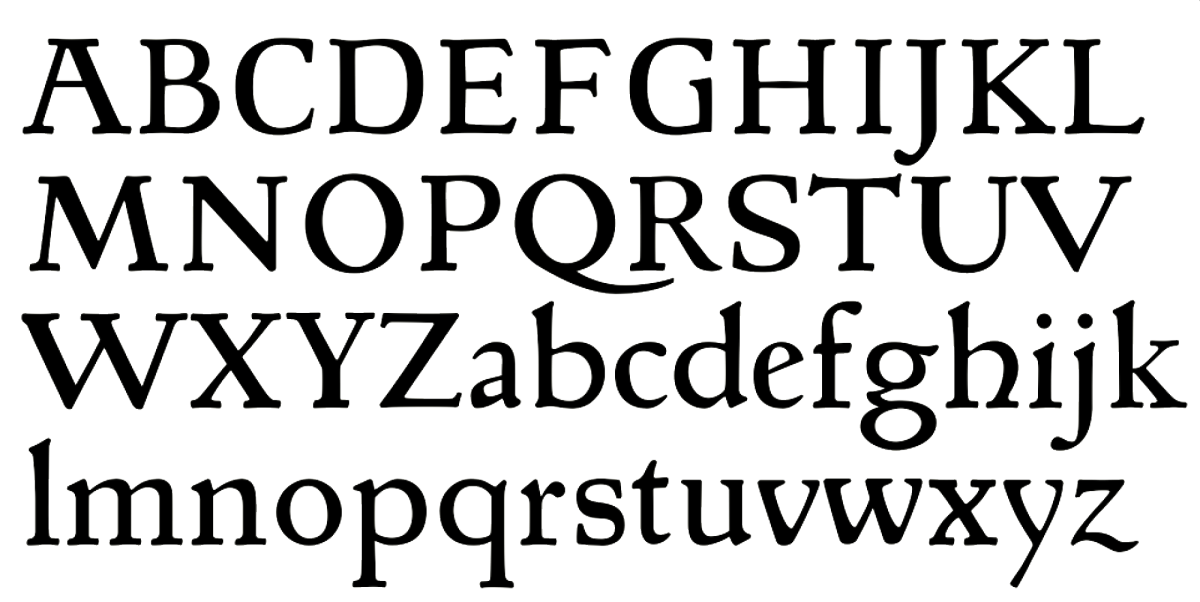
Tipo de Ulrich Gering de 1476: ejercicio de rescate histórico hecho por alumnos en taller dirigido por Alejandro Lo Celso y Philippe Millot, en la ENSAD École Nationale Supérieure des Arts Décoratifs, París, 2007.
Hubo varios intentos de rescate de este estilo: los célebres aunque poco felices tipos Troy y Chaucer de William Morris (fines del s. XIX); el revival del propio tipo de Subiaco hecho por St. John Hornby para su imprenta londinense Ashendene en 1902; el tipo Treyford, una interpretación literal de la caligrafía de Petrarca, diseñado por Graily Hewitt para la imprenta de la Universidad de Oxford en 1929 (severamente desacreditado por Stanley Morison en The Fleuron VII, p.180). Las góticas romanizadas se usaron un breve período pero fueron pieza clave en la evolución de los estilos. Entre 1459 y 1485 se produjeron hermosos incunables en góticas romanizadas. E inmediatamente sucedió la gótica rotunda, de gran preferencia entre los impresores de España.
3 Gótica Rotunda. Este tercer grupo de góticas es la “versión” italiana de las góticas texturas, y al parecer fue muy popular en Florencia. Una letra francamente más redonda que la textura (letras c e o b d p q), sin su pie diagonal de base, y a diferencia de la tendencia humanística de las góticas romanizadas, la a está cerrada y la g adopta la típica forma angular, mientras ascendentes y descendentes se acortan bastante. Según Johnson el ámbito paleográfico les ha llamado letras “boloñesas” por su uso en la escuela de leyes de la Universidad de Bolonia, aunque también se les ha denominado “venecianas”. Para nosotros hoy “veneciana” significa “romana” en el sentido de las primeras antiguas humanísticas, como la romana de Nicolás Jenson. Sin embargo para el ojo del s. XV las góticas rotundas de Jenson eran mucho más familiares que su romana, una forma nueva y sofisticada a la que aun era preciso acostumbrarse. Johnson demuestra que, hacia el final del siglo, las góticas rotundas toman el lugar de las góticas romanizadas en los cuerpos pequeños, mientras que comienzan a competir con las góticas texturas en título y formas display.
Italia y las letras humanistas: de Petrarca a Bracciolini
Los estilos tipográficos que hoy llamamos humanistas surgieron como rescate de la legendaria minúscula carolingia del siglo VIII d.C. (en realidad de sus versiones tardías de siglos XI y XII), último momento de la historia europea al que los renacentistas veían asociada una cierta unidad político-cultural. Creada a pedido del emperador Carlo Magno por un grupo de eminentes calígrafos coordinados por el sajón Alcuino de York, la minúscula carolina fue impuesta como “estilo de la casa” por decreto imperial en el 789 d.C. Podríamos decir que se trata del primer “diseño de letra personalizado”.
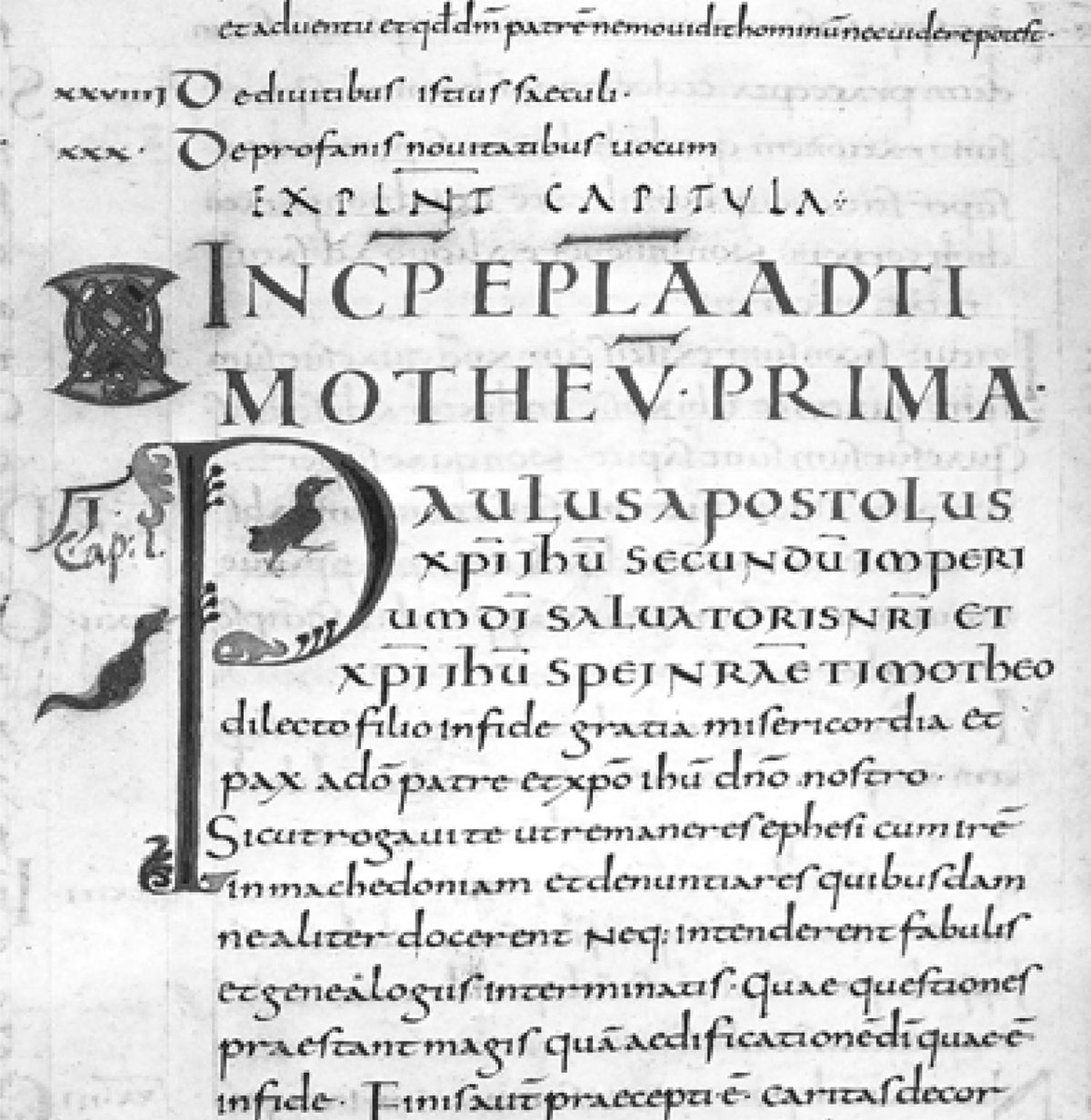
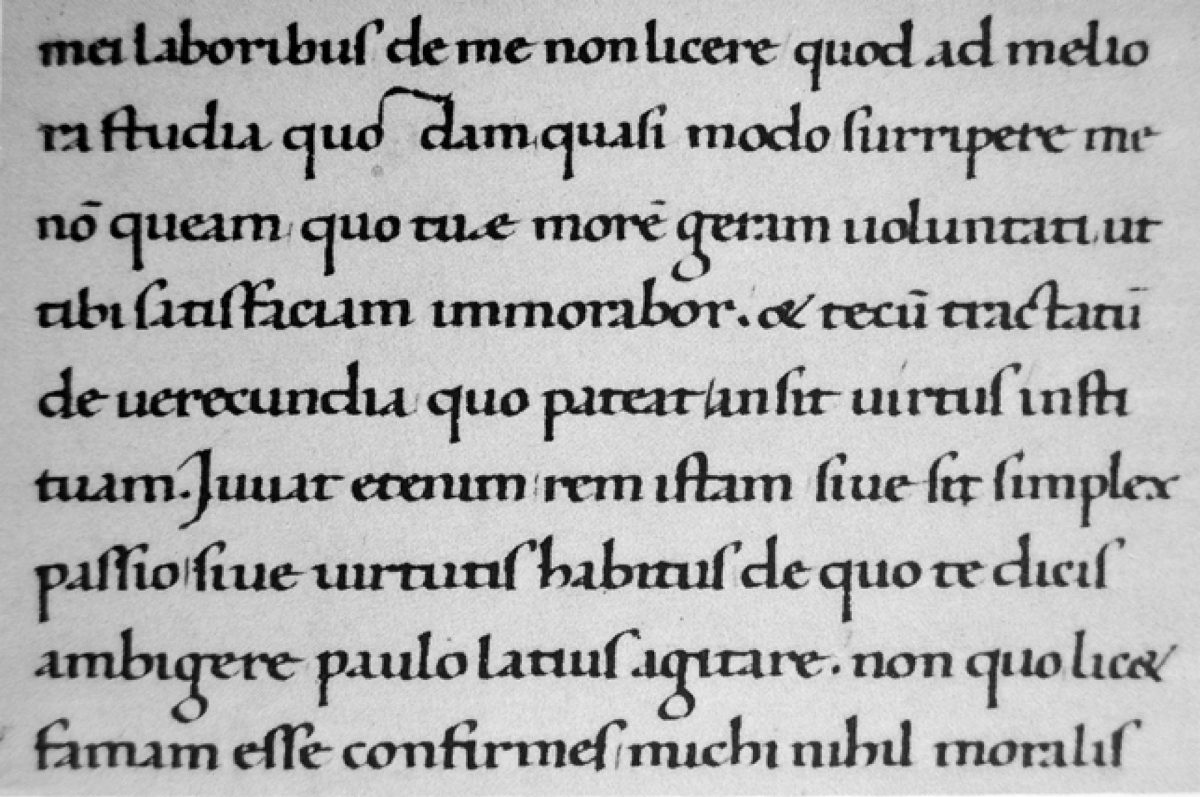
Petrarca (1304-1374) fue el precursor de esa admiración por la carolingia, la reflejó en su propia letra de copista y la llamó “lettera antica” en oposición a los modelos medievales vigentes en su época. A partir de su influencia y la de sus discípulos –Coluccio Salutati (1330-1406), discípulo de Petrarca; y Poggio Bracciolini (1380-1459), discípulo de Coluccio–, los estilos caligráficos de los manuscritos italianos del siglo XV, inspirados en los manuscritos carolingios, alcanzaron singular belleza, demostrando la devoción de los humanistas al combinar sus ideales románticos con sus capacidades artísticas. Hacia 1400 Poggio Bracciolini escribe una nueva lettera humanistica, muy inspirada en las carolingias de los siglos XI y XII. De acuerdo a Donald Anderson 4, ese es el corazón de nuestro alfabeto minúsculo. Sin apuro este estilo convivió durante casi un siglo con la gótica rotunda y con varios estilos de bastarda, una gótica itálica típicamente francesa.
La segunda aportación de Poggio es altamente valiosa. Como es sabido, el estudio de las mayúsculas obsesionó a los renacentistas. Con la idea de alcanzar la letra “perfecta” arquitectos, artistas y diseñadores buscaron (en todos los casos forzadamente) amoldar las estructuras de las capitales a retículas geométricas: Feliciano, Alberti, Da Moyle, Schedel, Pacioli, Fanti, Torniello, Durero, Verini, Tory, Tagliente, Palatino, Neudörffer, Fugger, Wyss, Yciar, Ruano, Cresci, Horfei, Rossi y Antonozzi son los nombres significativos de esos esfuerzos entre el siglo XV y el XVII. 5
De cualquier modo es evidente que estas mayúsculas, construidas a partir de proporciones geométricas (o más bien a la inversa), más que letras eran intelectualizaciones de letras. Sus contornos eran dibujados y luego rellenados de tinta. No era posible escribirlas en manuscritos. De acuerdo a Anderson, Poggio Bracciolini es quien, después de estudiar las capitales talladas en inscripciones epigráficas, desarrolla una versión caligráfica, en una escala apropiada para las minúsculas y trazadas con la misma pluma. Esto es un hito fundamental en la historia del alfabeto romano: mayúsculas y minúsculas comienzan a convivir en una página como dos subsistemas de escritura.
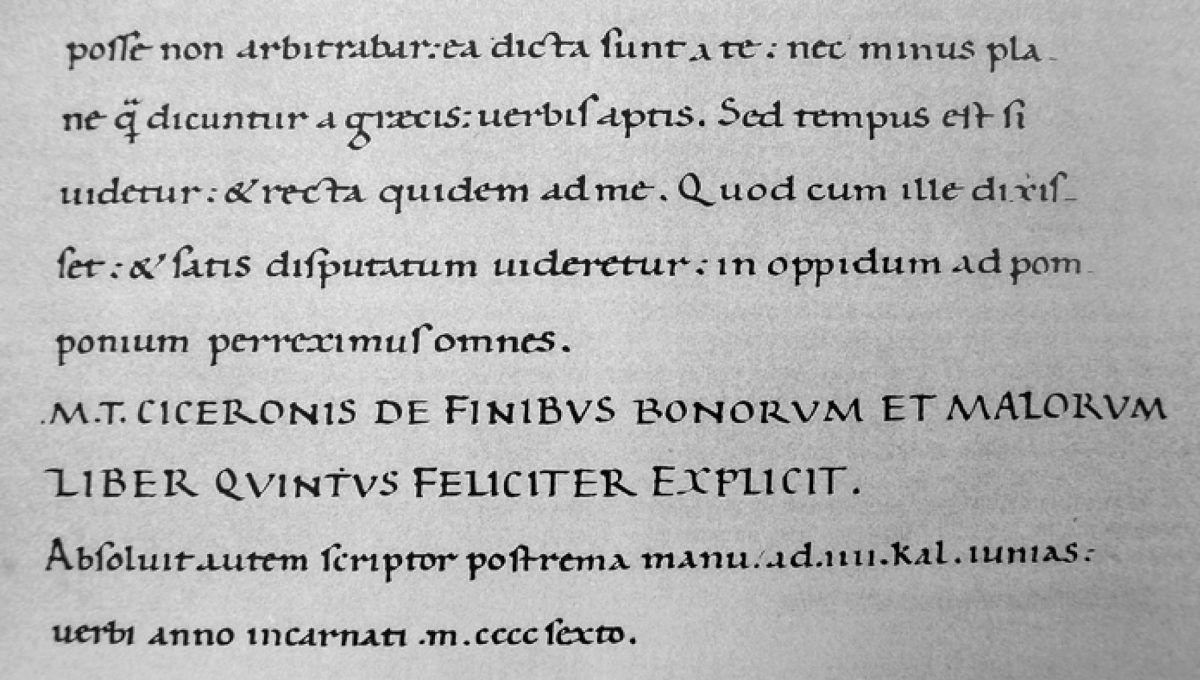
La itálica de Niccolò Niccoli
El comercio floreciente de libros manuscritos creó en Italia un sistema de fama y prestigio para los editores de libros así como para los escribas que eran empleados en las casas editoriales. Entre los nombres asociados a la minúscula humanística está también el de Niccolò Niccoli (1363-1437), quien al permitirse introducir en la minúscula cierta rapidez y espontaneidad logró el estilo que hoy denominamos “itálica”. Niccoli y Poggio abrieron así el camino a las dos interpretaciones de la minúscula humanística que se convertirían en los dos grandes estilos italianos del siglo XV, base de nuestra escritura tipográfica: la redonda y la cursiva.
Otros maestros escribas como Pietro Cennini (1462-1481) y Antonio Sinibaldi (1443-1528), ambos de Florencia, Marcus de Cribellarus de Venecia y, más notablemente, Bartolomeo Sanvito de Padua (1435- c.1520), contribuyeron al refinamiento de una caligrafía cursiva. Esta cursiva encontraría en 1500, por iniciativa de Aldo Manucio en Venecia, su primer molde en tipos de metal.6 Adobe Sanvito, una agraciada itálica humanista apenas inclinada, es homenaje de Robert Slimbach al gran calígrafo Bartolomeo Sanvito.
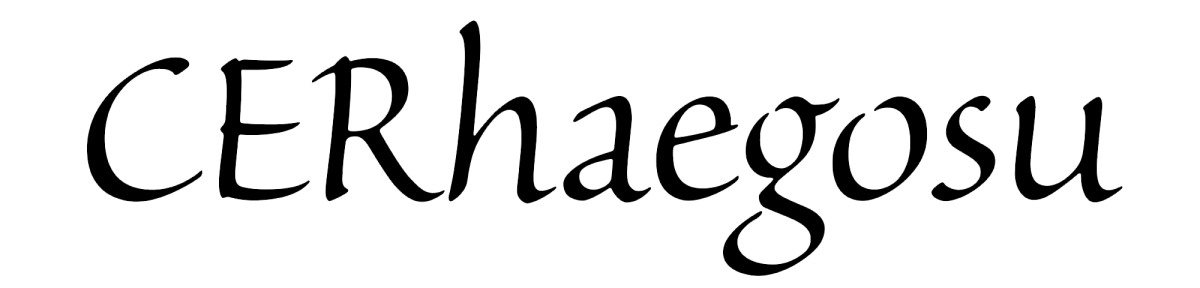
Adobe Sanvito, 1993, tributo de Robert Slimbach al calígrafo renacentista Bartolomeo Sanvito.
La escuela veneciana y Nicolás Jenson
Se cree que antes de 1500 ya había imprentas en unas 75 poblaciones italianas. Pero era Venecia la que ofrecía el mayor atractivo para los impresores. Una ciudad refinada y próspera en su comercio con Oriente, donde había importantes bibliotecas y residían muchos coleccionistas de manuscritos. Enviado por su protector el rey Carlos VII de Francia para interiorizarse con el arte negro en Maguncia, el francés Nicolás Jenson se encontró de regreso en París con una doble mala noticia: Carlos VII había muerto y su hijo el nuevo rey Luis XI no se interesó en admitirlo en la corte. En 1470 Jenson se establece en Venecia, y en poco tiempo se convierte en uno de los impresores más admirados.
Si bien hubo varios intentos de producir tipos en base a estilos caligráficos de la época –los hermanos alemanes Juan y Wendelin de Spira así como el mismo Jenson produjeron varias rotundas admirables–, es claro que la minúscula humanista era percibida como el estilo más apropiado para ediciones escolásticas.
De todos los intentos de colar un tipo en plomo que interpretase fielmente el espíritu de la mínúscula humanística es el de Nicolás Jenson el más logrado. Jenson abrió los espacios dentro y fuera de las letras y les dio a las contraformas un agradable efecto sereno y orgánico, obteniendo un ritmo muy armónico en la línea de texto y en la mancha tipográfica. Hasta su muerte en 1480, Jenson imprimió unos 150 libros, algunos extremadamente bellos, y sus páginas son hoy para muchos las más hermosas de la historia del libro occidental.
Por ser tan admiradas, ha habido innumerables rescates históricos de las venecianas. El talentoso Frederic Goudy se dedicó con fervor a ello. Sus tipos Deepdene y Berkeley Old Style son hermosos ejemplos de venecianas, interpretadas con el sentido de amigabilidad tan típico de Goudy. 7
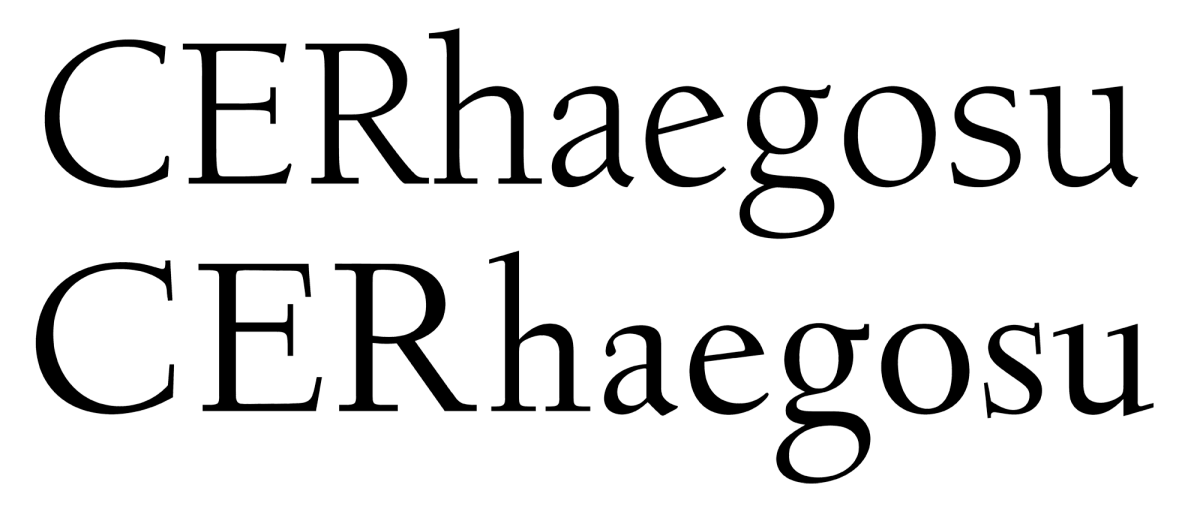
Dos grandes diseños de Frederic Goudy de inspiración veneciana: Berkeley Old Style [1914, versión digital ITC + Adobe 1989] y Deepdene [1927, versión digital Lanston 1992].
La veneciana de Jenson en particular también ha sido muy revisitada. Ya mencionamos los intentos (poco logrados) de William Morris.
El tipo Centaur del norteamericano Bruce Rogers (1870-1957) ha sido el más citado en la literatura tipográfica del siglo XX, aunque a nuestros ojos resulta inocente, por construir una letra aun más caligráfica que la del propio original. 8
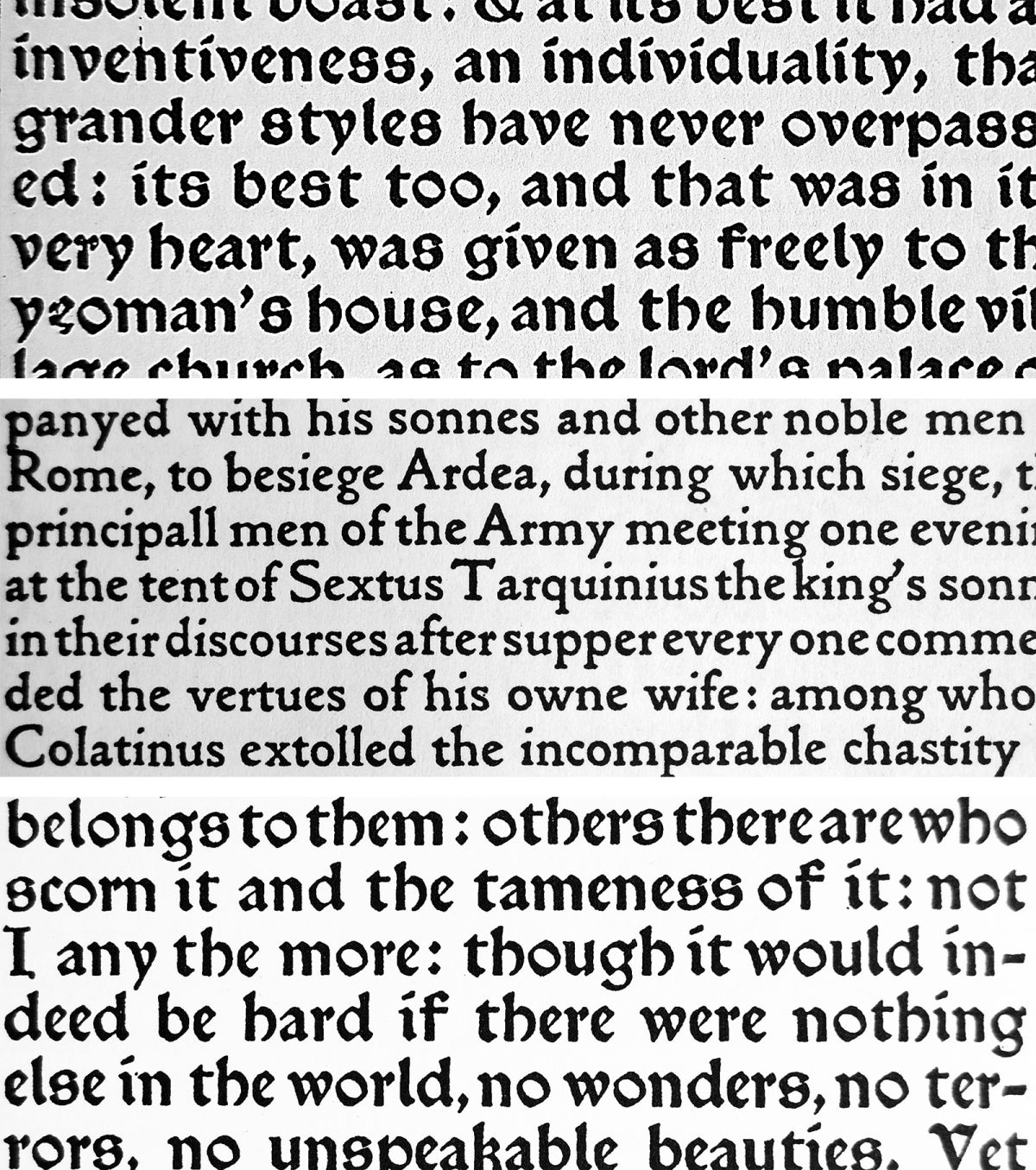
La interpretación digital de Robert Slimbach, Adobe Jenson, nos parece más justa con el espíritu jensoniano a la vez que más apropiada a ojos contemporáneos. Finalmente, una inquietante interpretación contemporánea es el tipo Lucrecia (no publicado) de Óscar Yáñez, egresado de la Maestría de diseño tipográfico del Centro Gestalt de Veracruz, México, 2007.
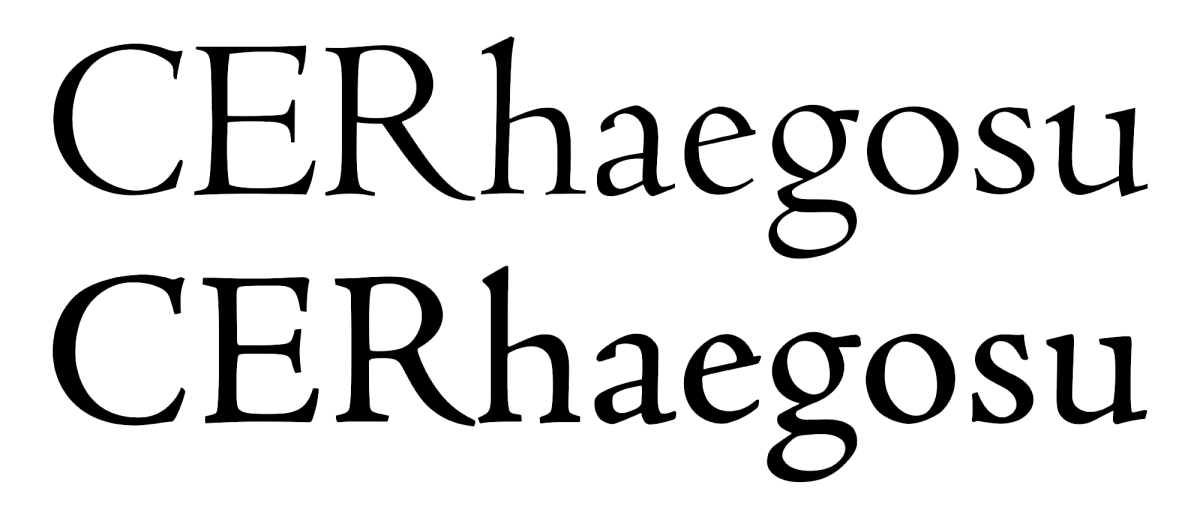
Monotype Centaur, de Bruce Rogers, 1915 [versión digital de Adobe, 1991] y Adobe Jenson de Robert Slimbach, 2000.
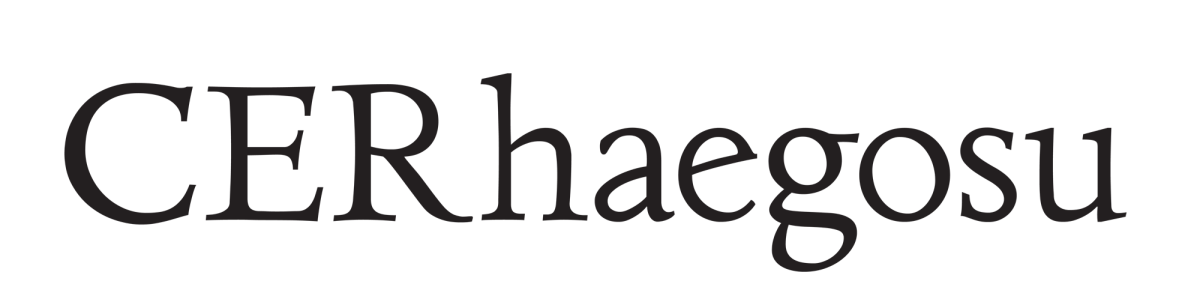
Tipo Lucrecia de Óscar Yáñez, 2007 [no publicado].
Francesco Griffo y la imprenta aldina
Aldo Manucio es con justicia recordado como el “Príncipe de la Imprenta”, por la belleza y refinamiento de sus ediciones y por la importancia de las innovaciones editoriales que introdujo. En 1495 estableció su taller en Venecia e inmediatamente publicó, nada menos que, los primeros libros impresos en griego. También en 1495 Manucio publica la obra De Aetna del cardenal Pietro Bembo (personaje central del intelecto veneciano y autor de las celebradas cartas románticas a Lucrecia de Borgia). Para este libro Aldo contrata los servicios del joyero de Bolonia, Francesco Griffo, quien graba los caracteres que hoy conocemos como tipografía Bembo (la de Monotype por ejemplo). Cuatro años más tarde la sensibilidad de Griffo con la letra humanística estaba más depurada. Su nuevo diseño (hoy Poliphilus) se usó en la renombrada obra de Francesco Colonna, Hypnerothomacchia Poliphili, obra mítica del Renacimiento. Por vez primera en un impreso las capitales (de inspiración epigráfica) estaban bien armonizadas con las minúsculas, logrando un bello ritmo blanquinegro en la línea de texto. Además las ilustraciones estaban armonizadas con las manchas de texto, logrando un efecto único.
El paso de Jenson a Griffo aportó dos aspectos anatómicos importantes: por un lado, un tipo de letra más independiente de los modelos caligráficos; si la redonda de Jenson estaba más cerca de la minúscula humanística de Petrarca y Poggio, la redonda de Griffo daba un paso hacia una forma más “escultórica”, más vinculada a la nueva manera de producir un texto: grabando cada caracter en el extremo de un punzón de acero, el punzón martillado en la superficie plana de una matriz de cobre, la matriz alojada en el interior de un molde de hierro fundido, donde se vertía fundición líquida de plomo que, al secar, resultaba en un tipo de metal. Por otro lado, Jenson había alineado los serifs de los ascendentes con la altura de mayúsculas. Griffo elevó ligeramente los remates de ascendentes de modo de alinear las mayúsculas con las contraformas inferiores de esos remates. Ese detalle llegó para quedarse en la anatomía tipográfica pues volvía más elegante el contraste rítmico entre mayúsculas y minúsculas. Las letras de Griffo son la base de las letras antiguas, y las letras antiguas son las que la humanidad ha estado leyendo durante más tiempo. Su elegancia, color y legibilidad constituyeron un nuevo y alto estándar en la industria editorial de su tiempo.
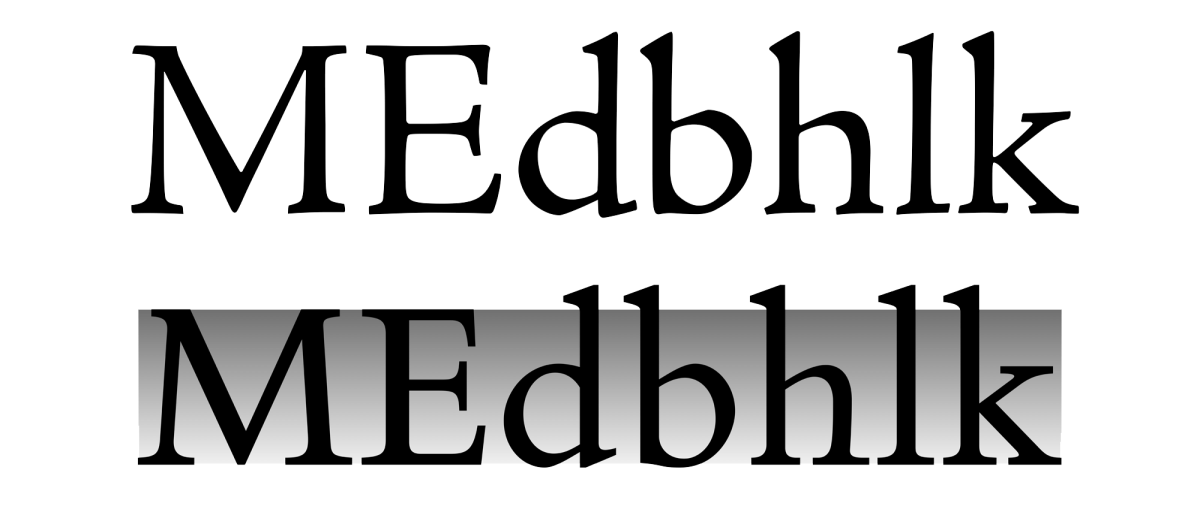
Adobe Jenson versus MT Bembo [comparar formas, y alineación de ascendentes y capitales].
A la par de la obra de Griffo y Manucio hubo otro alfabeto romano de gran calidad, el grabado hacia 1486 en Venecia por el alemán Erhard Ratdolt (1447-1528). Pero Ratdolt no tuvo en su época la difusión que tuvo Griffo bajo el sello de la imprenta aldina. No obstante esa difusión Aldo nunca reconoció oficialmente la autoría de Francesco sobre las letras, asunto que originó el distanciamiento entre ambos. 9
Giovanni Mardersteig es quien investigó vida y obra de Griffo a profundidad, y lo reflejó en un extenso artículo: “Aldo Manuzio e i caratteri di Francesco Griffo da Bologna”. Existen varios revivals digitales de la obra de Francesco: Aetna de Jack Yan, Griffo Classico de Franko Luin, o la Bitstream Aldine 401. En un excelente artículo Charles Bigelow y Jonathan Seybold 10 han comparado cuatro sucesivos intentos de rescate de Griffo: en 1923 la Monotype produjo Poliphilus: una copia literal de impresos de Aldo que reproducía vanamente los bordes erosionados de las letras (figuras A y B abajo). En 1929 Stanley Morison entusiasmó a la compañía con la idea de Bembo, basada en el tipo de Griffo para De Aetna. El resultado fue mejor, se neutralizaron las erosiones e irregularidades propias de la impresión original (figura C). Quizás como un experimento, al año siguiente Morison invita al gran impresor alemán Giovanni Mardersteig (1892-1977) a realizar un nuevo rescate del tipo de De Aetna, pero esta vez los punzones grabados a mano por el talentoso Charles Malin. Después de 6 meses de trabajo conjunto el resultado (llamado Griffo) estuvo mucho más cerca del original (figura D). Finalmente en 1955 Mardersteig realizaría Dante, su propia interpretación de Griffo, los punzones igualmente grabados por Malin. Un gran diseño que Mardersteig mismo utilizó profusamente en libros editados en su Officina Bodoni (figura E). Extendiendo la misma idea de comparación de Bigelow y Seybold, la versión más contemporánea, MT Bembo Book Pro (2005, figura F) luce más armónica en dibujo de curvas, modulación y color general.
Nacen las primeras itálicas
Manucio y Griffo colaron en plomo la primera tipografía itálica. Los libros resultaban excesivamente grandes cuando se componían en romanas, cuyo cuerpo rondaba los 16 puntos. Aldo deseaba un libro de bolsillo que resultara más atractivo a los compradores. Para ello Griffo hizo la nueva itálica basándose en una cursiva humanística estrecha y de poca inclinación, y le dio un cuerpo de unos 12 puntos. Sus capitales fueron las primeras “versalitas” de la historia, los ascendentes de minúsculas sobrepasaban largamente la altura de mayúsculas.
Hubo muchos ensayos y errores en el camino hacia una cursiva apropiada para lectura. Su cercanía con la caligrafía planteaba la dificultad de hasta dónde reproducir la conectividad natural de una escritura manual. Como comenta Updike 11 la tipografía itálica no fue verdaderamente exitosa entre los impresores hasta que no se independizó totalmente de sus orígenes caligráficos. Pero el nombre más importante en la búsqueda de una itálica fundida es sin duda el de Ludovico Vicentino degli Arrighi, el gran escriba del Vaticano.
Para su propio manual de escritura de 1523 Vicentino “diseñó” una cursiva imitando su propia cancilleresca (grabada por un joyero de Perugia, Lautitio di Meo), y más tarde la perfeccionó en una segunda versión que ha sido de gran inspiración en la historia.
El refinamiento de París y Lyon
Entre 1530 y 1600 tuvo lugar el período más rico y significativo de la historia de la producción tipográfica. Por ello no es casual que la literatura habitualmente se extienda sobre la escuela francesa, protagonista de esa edad de oro de las letras de imprenta. Basándose en el estilo aldino los franceses supieron refinar y acuñar el suyo propio, que fue la base para los diseños de siglos subsiguientes.
Los primeros impresores en Francia también fueron alemanes. La tradición cita al trío Freiburger, Gering, Kranz como los primeros. Contratados por La Sorbona hacia 1470 a instancias del progresista germano Juan Heynlin, ex-rector de la casa, los tres alemanes grabaron algunos tipos góticos con los que imprimieron varios clásicos para la universidad. A partir de 1472 se independizan bajo el célebre sello El Sol de Oro en la calle Saint Jacques, donde más tarde Ulrich Gering solo, graba unos tipos góticos romanizados muy bellos (ver más arriba).
En lo que toca a góticas vernáculas, en 1477 Pasquier Bonhomme funde en plomo la primera gótica bastarda, una letra cursiva inspirada en los manuscritos de época del Norte de Francia, que se asoció rápidamente al idioma francés como contrapunto de las góticas verticales, usadas para el latín.
El uso de góticas vernáculas y el gusto por una profusa ornamentación en página, en manos de impresores como Tory, Du Pré, Le Rouge, Pigouchet, Vostre y Vérard, colocan muy alto la calidad y originalidad de los incunables franceses, no sólo provenientes de París sino también de Lyon.
Geofroy Tory (1480-1533) merece un párrafo especial en esta historia. Su famosa obra Champfleury o Arte y ciencia de la verdadera proporcion de las letras, publicada en 1529, tuvo una enorme influencia en la época. Como mencionamos más arriba obsesionaba a los renacentistas la idea de forzar la estructura de las letras a esquemas geométricos y su construcción a supuestos procedimientos algebraicos. Las ideas de Tory eran de un aun más poderoso sentido místico. Relacionó la proporción de 1/10 con Apolo y las nueve musas, y afirmaba que la diosa Io regía la construcción de todas las letras, por componerse su nombre (I - o) de los dos elementos básicos de un alfabeto mayúsculo. Pero la ingenuidad de estas asociaciones no debe empañar el gran valor del Champfleury, tanto un estudio de la construcción de las mayúsculas como también un tratado de arte tipográfico que contribuyó a la consolidación de la gramática y ortografía francesas y afirmó la introducción de una estética clásica asociada a la letra romana en oposición a la gótica. 12
Con París como nuevo centro económico pujante, los impresores y tipógrafos franceses del siglo XVI comienzan a aportar su propia visión a la tradición humanista. Simon de Coline (1480-1547) y Antoine Augereau (1490-1534) son importantes pues inician con sus ediciones un estilo francés característico. Claude Garamond (1490-1561, aprendiz de Augereau) es importante por ser el primero que se especializa en grabar punzones y fundir tipos de plomo para impresores, a la vez que por hacer una interpretación del estilo de Griffo con un sabor muy francés. Bajo la dirección artística del gran editor parisino Robert Estienne (1503-1559), autor de hermosas biblias y críticas de textos clásicos, Garamond graba una letra de una delicadeza más culinaria y lírica, pero sobria, autocontenida y bien proporcionada para libros. La letra de Garamond se convertiría con el tiempo en la más ubicua de la historia occidental. Es justo reconocer, a la par del trabajo de los creadores de tipos, el trabajo de quienes promovieron esos tipos. Así, Henri Estienne (padre de Robert) difundió en sus ediciones los tipos de Simon de Coline y Augereau, igual que Robert Estienne lo hizo con los tipos de Garamond. La letra de Garamond probablemente no habría llegado tan lejos sin el asesoramiento de Robert, ni tampoco sin la difusión que le dieron sus hermosas ediciones. Esa suerte de entusiasmo colectivo permitió acuñar en pocos años un estilo nacional característico.
Las Garamonds
Justamente por ser Garamond la tipografía más revisitada, existe una gran variedad de versiones. Hay Garamonds muy respetuosas de la fuente original: en Garamond Premier, Robert Slimbach hace una interpretación refinada de los punzones (hoy en el museo Plantin-Moretus de Amberes) e inspirándose para las cursivas en el trabajo de Robert Granjon. Hay Garamonds que no lo son: la Monotype Garamond basada en los Caractères de l’Université diseñados por Jean Jannon, como demostró Beatrice Warde en 1926, y que constituyen la primera romana garalda barroca. 13
Hay Garamonds de fuerte impronta cultural no-francesa: la versión Pop de Garamond que Tony Stan hizo en 1977 para la ITC, de tono alegre y despreocupado, muy distante del original. Por otro lado la germánica Garamond de Stempel de 1925, cuyos ángulos dramáticos evidencian la influencia gótica. La Linotype Sabon de 1967, interpretación igualmente germánica de un maduro Jan Tschichold, quien le da proporciones cuadradas e igualitarias a los caracteres 14; y la re-visita digital de Sabon: Sabon Next (2008), que la misma Linotype encargó al tipógrafo francés Jean-François Porchez y que recupera las proporciones, las especias, el sabor galo original.
Las Garamond quizás más emblemáticas:
1 Adobe Garamond Premier de Robert Slimbach, 2005.
2 Monotype Garamond [Jean Jannon, 1621. Reivindicado su origen por Beatrice Warde en 1955].
3 ITC Garamond de Tony Stan, 1975, digitalizada por EF en 1998.
4 Stempel Garamond.
5 Linotype Sabon, de Jan Tschichold, 1967.
6 Linotype Sabon Next, de Jean-François Porchez, 2004.
A otro punzonista y fundidor parisino, Pierre Haultin (1515-1597), debemos el primer diseño ligeramente condensado y de una caja de x más alta, una forma que se identificará más tarde como el “gusto holandés”. En su línea más pragmática de pensamiento y con la idea de reducir el formato de las biblias –un protestante en un país católico debía prever una huida rápida–, Haultin grabará también la primera letra diminuta (cercano a los 6 pt), que sería la más pequeña por mucho tiempo. 15
El más grande de todos los punzonistas
Es sin duda Robert Granjon (1512-1590) la figura central de la tipografía renacentista, y quizás de toda la historia tipográfica europea. Su obra es la más prolífica, innovadora e influyente. Hijo del impresor parisino Jean Granjon, Robert publica algunos libros entre 1549 y 1562 y luego se entrega por completo al grabado de punzones. Vive en Lyon, París, Génova, Frankfurt, Amberes (donde graba punzones para Christophe Plantin), y finalmente en Roma trabajando para la Imprenta Vaticana donde termina sus días a la edad de 77 años 16 Su obra comprende 27 itálicas, 13 redondas, 7 civilités (basadas en la lírica caligrafía gótica de moda en el Norte de Europa), 9 alfabetos griegos, 12 orientales, 6 tipos para música y gran cantidad de arabescos, ornamentos, florones e iniciales. Según el historiador John Lane, fundidores de todos los países continuaron colando tipos de matrices granjonianas hasta fines del siglo XVIII. 17
Granjon quiebra la tradición itálica aldina al introducir en 1543 las primeras mayúsculas inclinadas. Sus mayúsculas son también más pequeñas, y los trazos poseen ángulos dramáticos muy armoniosos. Granjon es el maestro del contrapunto. Por lo mismo sus cursivas son las más admiradas. 18 Galliard (1978) de Matthew Carter (1937), excelente interpretación del estilo de Granjon, es resultado de un estudio integral de toda su obra más que de un cuerpo tipográfico determinado. 19
ITC Galliard, de Matthew Carter, 1981 [versión digital Adobe 1990].
Una de las tantas itálicas basadas en alguno de los estilos de Robert Granjon: Adobe Garamond Premier de Robert Slimbach, 2005.
Hacia 1560 Christophe Plantin (1514–1589), refinado impresor francés, se instala en el centro cultural más importante del norte europeo, Amberes, donde ya florecía la industria del libro. A lo largo de su vida Plantin, apasionado por la tipografía, encargó y coleccionó tipos de los grandes diseñadores de letras (en su mayoría franceses), contribuyendo a diseminar estos diseños por todo el Norte de Europa. Su imprenta llegó a tener 22 establecimientos y se le cosidera el primer impresor en escala industrial. En el Museo Plantin-Moretus de Amberes se encuentra gran parte de su obra más todo el material tipográfico de Plantin y de sus descendientes. 20
Además de Perre Haultin y de Robert Granjon, los franceses François Guyot, Guillaume I Le Bé y los herederos de Garamond, el flamenco Ameet Tavernier y el belga Hendrik van den Keere proveyeron de tipos a la imprenta de Christophe Plantin. François Guyot (?-1570), parisino de origen, vivió en Amberes entre 1540 y 1570, y grabó para Plantin unos tipos muy bellos que se usaron por toda Europa durante largo tiempo. Ameet Tavernier, de Bailleul (frontera norte con Bélgica) grabó punzones para la Officina Plantiniana entre 1555 y 1561, incluida la primera itálica que habría utilizado Plantin. Sus redondas se asemejan a Garamond y sus itálicas posteriores a Granjon.
Hacia fines del siglo XVI con Amberes y Haarlem destacándose en producción editorial, surge el momento de los Países Bajos, lo que inicia un nuevo capítulo en la historia del diseño de tipografías.
Continúa en La Herencia Europea. Parte II
- Es preciso destacar la tarea que la editorial valenciana Campgràfìc realiza desde hace años editando en castellano obras tipográficas de valor. Asimismo tanto en Brasil como en México esfuerzos independientes han editado en los respectivos idiomas Los elementos del estilo tipográfico de Robert Bringhurst, referencia bibliográfica fundamental. Y también el Círculo de Tipógrafos de México ha iniciado su camino editorial con un libro sobre Jan van Krimpen. ↩
- A. F. Johnson, Type Designs. ↩
- Tomamos prestado el término “display” del idioma inglés por no existir uno equivalente en español o portugués. El término “título” es muy específico y poco abarcativo, mientras “tipografía display” refiere toda situación de uso tipográfico donde no hay lectura inmersiva: típicamente en carteles, envases, rótulos de negocios, vehículos, portadas de libros, títulos en diarios y revistas. Para componer lectura prolongada o inmersiva utilizamos tipografías “para texto”. Ver cuadro “Texto versus Display”. ↩
- Donald M. Anderson, Calligraphy, p.113. ↩
- Anderson describe la secuencia de forma pormenorizada, Calligraphy, pp.125-133. Otros referentes valiosos sobre este tema son: Giovanni Mardersteig, “Leon Battista Alberti e la rinascita del carattere lapidario romano nel Quatrocento”; Matthew Carter, “Theories of Letterform Construction. Part 1”; y James Mosley, “Giovan Francesco Cresci and the Baroque Letter in Rome”. Referencias bibliográficas completas al final del texto. ↩
- Ver “Nacen las primeras itálicas”. ↩
- La obra de Goudy es una de las más prolíficas y fundamentales de la historia. Para comprender su filosofía de diseño resultan valiosos sus libros Typologia y Goudy’s Type Designs. Y sobre su accidentada vida, Behind the type de Bernard Lewis es una buena biografía. El propio Goudy publicó entre 1918 y 1926 la revista Ars Typographica, reimpresa por Greenwood Press en 1970. ↩
- Mientras la letra de Jenson resultó directamente del grabado de punzones de acero, Bruce Rogers trabajó sobre ampliaciones fotográficas de las páginas de Jenson, re-escribiendo los signos con una pluma de punta plana. Esto explica el espíritu caligráfico resultante, distante del original. Rogers narra la historia de su diseño en The Centaur Types. Para apreciar su exquisita obra como diseñador de libros: Joseph Blumenthal, Bruce Rogers, a life in letters. ↩
- Luego de dejar a Aldo, Griffo regresa a Bolonia y graba punzones para el impresor Geronimo Soncino y para sí mismo. Pero desde 1518 su rastro se pierde. En una discusión con su yerno, Griffo le habría provocado la muerte clavándole un punzón o una lima en la frente. Se desconoce el final de la historia, no habiendo registro oficial que pruebe si fue ahorcado como pena por su delito. ↩
- Charles Bigelow y Jonathan Seybold, “Technology and the aesthetics of type – maintaining the tradition in the age of electronics”, The Seybold Report, vol.10, no.24, 1981, p.5. ↩
- D.B. Updike, Printing Types (1922), p.130 (de la 4ta edición: 2001) ↩
- Geofroy Tory, Champfleury, edición facsimilar de Bibliothèque de l’Image. El prefacio de Paul-Marie Grinevald, ex bibliotecario de la Imprenta Nacional de Francia, es lúcido y esclarecedor. ↩
- Paul Beaujon (seudónimo de Beatrice), “The ‘Garamond’ Types: A Study of XVI and XVII century sources”, The Fleuron V (pp.131-179). La letra de Jannon (de 1621) tiene un nuevo vigor, un dinamismo e inquietud expresiva que es más característico del Barroco, y que se encuentra también en las itálicas de Robert Granjon. ↩
- El que redondas e itálicas ocuparan la misma caja de espacio se debía a una limitante de la teconología de linotipía que no permitía tener matrices de anchos independientes para un estilo y otro. ↩
- En su libro Counterpunch Fred Smeijers reivindica el protagonismo de Pierre Haultin, así como del belga Hendrik van den Keere, como dos grandes figuras de la tipografía neerlandesa. El libro describe varios aspectos del proceso de grabado de tipos y en particular el rol de los contrapunzones, punzones que se martillaban sobre punzones para obtener la contraforma. ↩
- Los tipos de un ya maduro Granjon embellecen las páginas del catálogo tipográfico del Vaticano, The Type Specimen of the Vatican Press, facsimil del original de 1628. ↩
- John Lane, Early Type Specimens, pág. 39. ↩
- Para las itálicas de Granjon consultar: Hendrik D.L. Vervliet, “The italics of Robert Granjon”, en Typography Papers 3, pp-5-59; el artículo de A. F. Johnson, “The italic types of Robert Granjon” en A. F. Johnson, Selected Essays on Books and Printing. Sobre la obra ulterior de Granjon en Roma ver: introducción de Vervliet a la edicion facsimilar del catálogo del Vaticano de 1628; y también H. D. L. Vervliet, Cyrillic & Oriental Typography. ↩